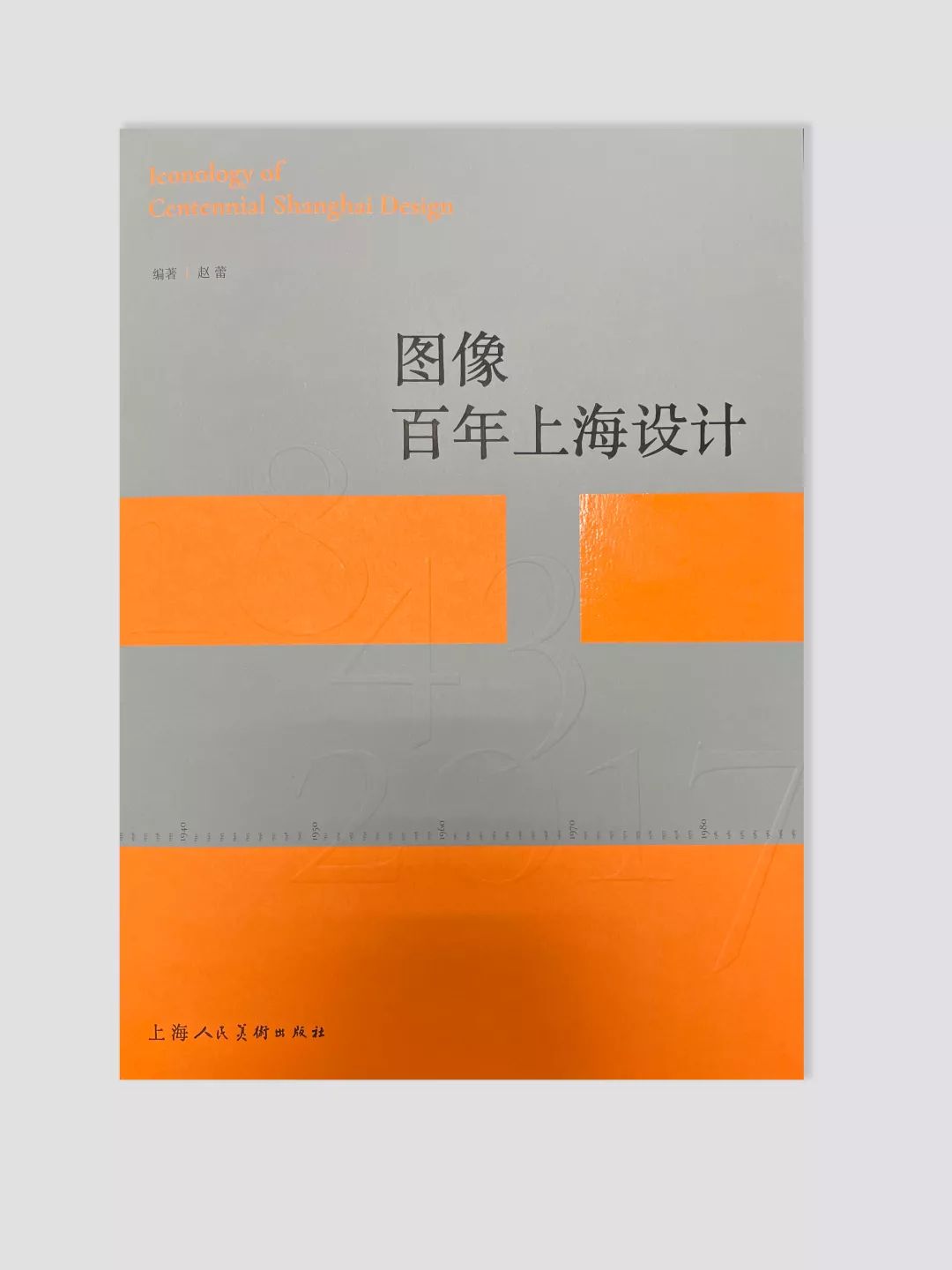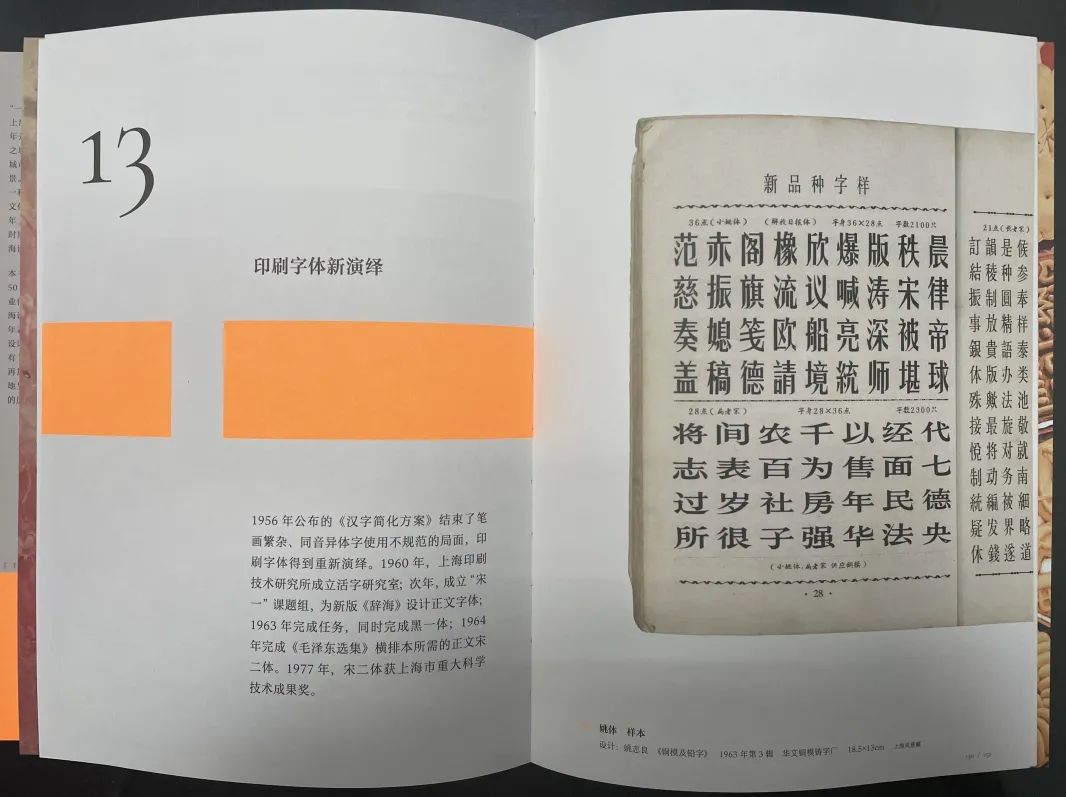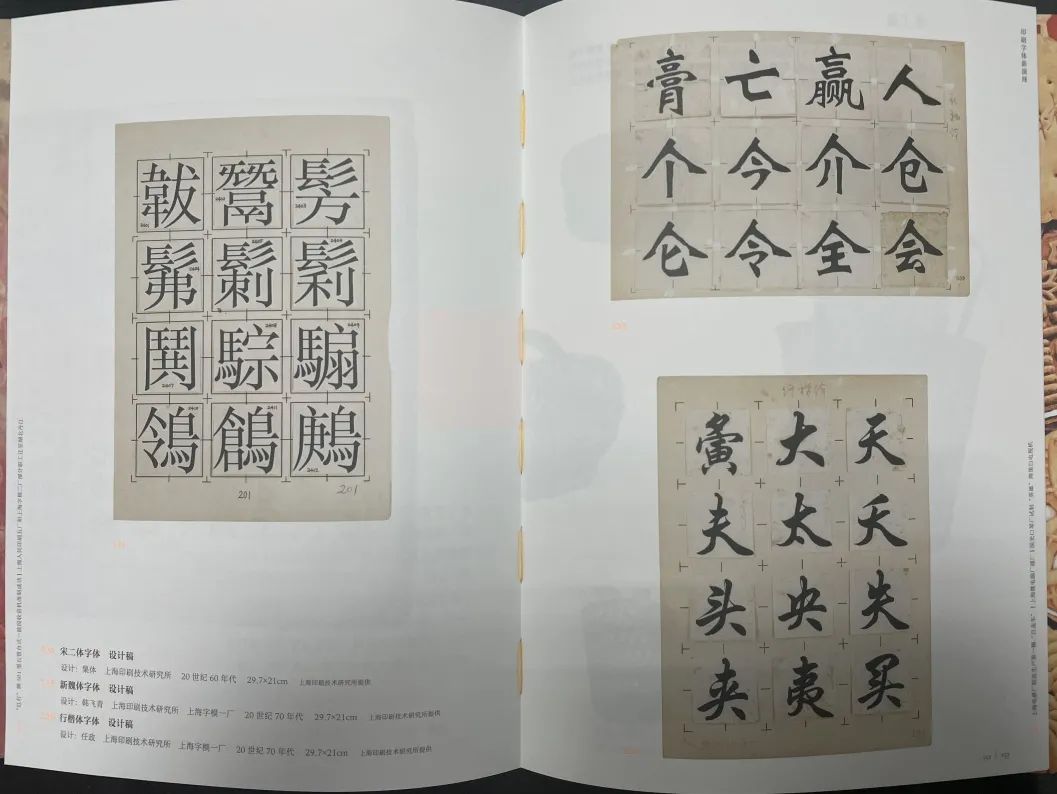
“一千年历史看北京,一百年历史看上海。”百年上海,百舸争流,东西汇聚,博约摩登。
自 1843年开埠以来,上海成为中国近现代进程中的都会之城,多元、包容、大气、谦和、精致、理性的城市气场得益于其得天独厚的地理条件与历史背景。“上海”之于中国不仅是一个地域名词,更是一种生活形态的象征;“上海”之于世界,是一种文化现象,更是一件独一无二的城市精神瑰宝。
《图像百年上海设计》收录的图文来自 2020 年金秋在刘海粟美术馆举办的“百年上海设计”展,其中包括围绕展览主题展开的四次研讨会实录。
“百年上海设计”展 2020年9月30日下午,由上海大学上海美术学院、上海刘海粟美术馆主办的“百年上海设计展”在刘海粟美术馆开幕。展览以时间为轴线,通过近300件不同类型的实物、手稿和文献,构成二十世纪前后上海设计样貌,其中涉及平面、产品、教育、机构等多个领域,也从中探讨设计背后的生活美学、商业理性和经济制度,发现塑造上海设计品质所需的人文与地理环境要素。 本书所用“图像百年上海设计”“汇流、奋进、开拓”字样出自上海印刷技术研究所提供的“宋二”字体设计原稿。 印研所提供的字稿 1956年公布的《汉字简化方案》结束了笔画繁杂、同音异体字使用不规范的局面,印刷字体得到重新演绎。1960年,上海印刷技术研究所成立活字研究室; 次年,成立"宋一"课题组,为新版《辞海》设计正文字体;1963年完成任务,同时完成黑一体; 1964 年完成《毛泽东选集》横排本所需的正文宋二体。 1977年,宋二体获上海市重大科学技术成果奖。 宋二体字体 设计稿 设计∶集体 上海印刷技术研究所 20世纪60年代 29.7×21cm 上海印刷技术研究所提供 新魏体字体 设计稿 设计∶韩飞青 上海印刷技术研究所 上海字模一厂 20世纪70年代 29.7×21cm 上海印刷技术研究所提供 行楷体字体 设计稿 设计∶任政 上海印刷技术研究所 上海字模一厂 20世纪 70年代 29.7×21cm 上海印刷技术研究所提供
装帧设计
全书使用5色印刷。 将虚线以“汇流”“奋进”“开拓”三个阶段的物品数量,拓展为三段长短不一的色块,并将此色块作为封面元素。 封面以及章节页上的“图像上海百年设计”“汇流”“奋进”“开拓”等字样,均出自上海印刷技术研究所提供的“宋二体”字体设计原稿。以透叠的形式保留了字稿设计的线框以及涂改液。 目录前三页精巧设计,书本上“图像百年上海设计”字样呈现出三种样式,每一页代表着字体当下设计形态,对应老一辈上海印刷技术研究所字体设计们,从最初在划线方格内设计字体,到设计过程当中细致的笔画修补,直至最终字稿成型。 书末附有信息图表设计,以字体、轻工业产品、平面及传播、商业、教育为线索,以时间为轴,将历史背景与设计事件纳入其中。
原标题:《图像百年上海设计》中的印刷字体新演绎